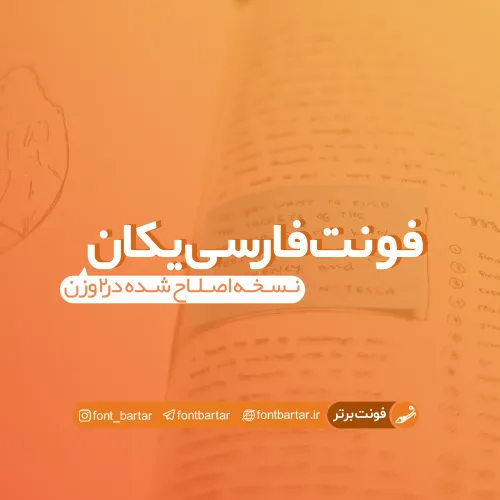
فونت فارسی یکان
فونت یکان از فونت های ممتاز فارسی است که کاربردهای بسیار زیادی در طراحی کتاب و پوستر دارد. از این فونت در کارهای رسمی متداولی استفاده شده است. برای نمونه کارت ملی از این فونت استفاده میکند.
طراح این فونت زیبا و بسیار خوانا گرافیست و هنرمند ایرانی مسعود سپهر است. وی این فونت را با الهام از فونت هوتیکا طراحی نمود. پس احتمالا این نخستین فونت بدون سریف فارسی است. البته ایشان تنها نسخه معمولی (Regular) این فونت را عرضه کردند. و نسخه ضخیم (Bold) آن بعدها توسط سایر طراحان عرضه شد.
اکنون نسخه اصلاح شده و بهینه شده این فونت منتشر شده است که در اجرا و خروجی بسیار بهینه تر عمل می کند و ۹۹% مشکلات ریز و درشت نسخه قبلی در این نسخه کاملا رفع شده و در چیدمان و سازگاری این فونت نیز هم اکنون کمی متفاوت تر عمل می کند.
فونت یکان مورد استفاده برای:
• طراحان وب سایت و گرافیست های خلاق می توانند از این مجموعه زیبا فونت در طراحی پروژه های تبلیغاتی و تجاری خود کمک بگیرند.